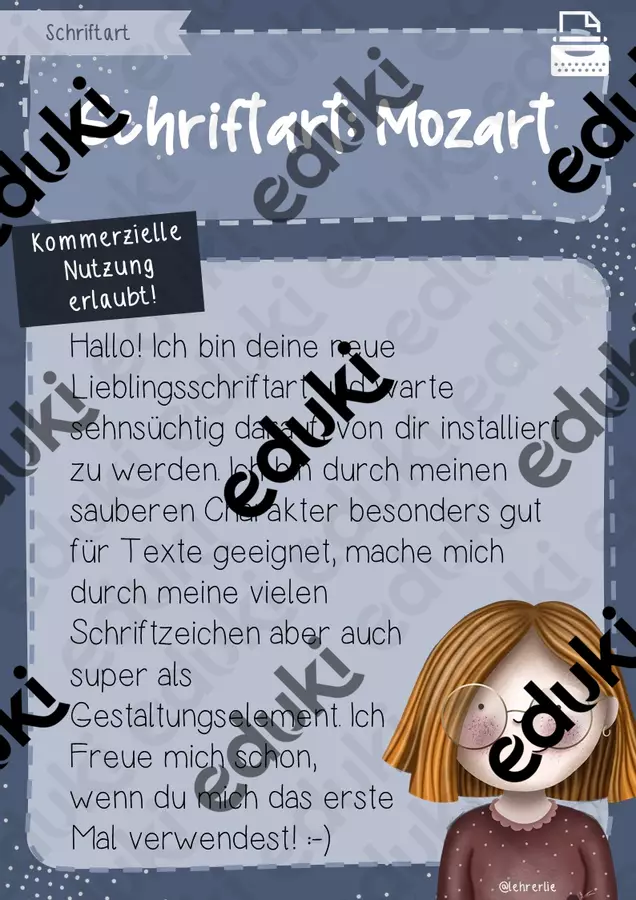
Und weiter geht es, mit den Komponisten-Schriftarten! Mozart bietet dir eine einfache, cleane Handschrift, die sich super für längere Texte und als Basic-Schriftart eignet. Sie hat einen extrem umfangreichen Zeichensatz und ist dementsprechend vielseitig einsetzbar.
Eine tolle Schriftart, vielen Dank! Ich habe nur gerade festgestellt, dass das kleine "a" in der Überschrift anders ist als in der restlichen Schrift - daran hatte ich mich beim Kauf orientiert -, sodass ich sie leider nicht für meine AB in Klasse eins nutzen kann. Dennoch eine wunderschöne Schrift, die ich auf jeden Fall nutzen werde :).